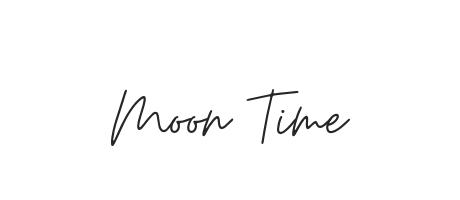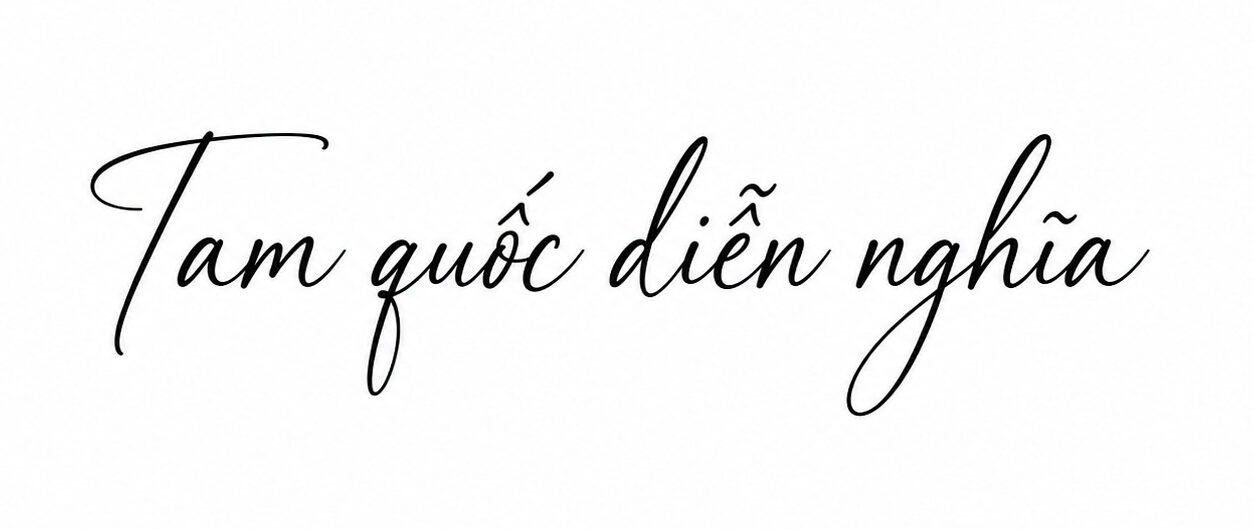
Font MoonTime là gì?
MoonTime font là một bộ phông chữ thuộc dòng Signature Script (chữ viết tay dạng chữ ký) mang phong cách nhẹ nhàng, phóng khoáng và tràn đầy cảm xúc lãng mạn. Được thiết kế với các đường tà chữ lướt nhanh, độ nghiêng nhẹ tự nhiên cùng các nét nối mềm mại, MoonTime mô phỏng chân thực cảm giác chấp bút từ ngòi bút mực kim thanh mảnh. Phông chữ mang lại vẻ ngoài tinh tế, tao nhã, giúp các sản phẩm thương mại dễ dàng tiếp cận người xem bằng sự mộc mạc và chân thành.
Trong nghệ thuật xây dựng thương hiệu thời trang và làm đẹp, MoonTime được ưa chuộng nhờ khả năng tạo điểm nhấn cá nhân độc đáo. Tuy nhiên, các nét vươn lên (ascenders) và kéo dài xuống (descenders) của bản gốc quốc tế thường bị va chạm với các dấu thanh tiếng Việt như dấu hỏi, ngã, nặng. Bản Việt hóa do In Viva chọn lọc đã được căn chỉnh khoảng cách an toàn cho hệ thống dấu tiếng Việt theo chuẩn Unicode, hỗ trợ nhà thiết kế dàn trang hài hòa mà không làm đứt gãy nhịp điệu tự nhiên của con chữ.
Lưu ý: MoonTime có cấu trúc nét chữ dạng chữ ký thanh mảnh. Khi thiết kế tiêu đề trên bề mặt bao bì tối màu, bạn nên ưu tiên kết hợp kỹ thuật ép kim nhũ vàng cát hoặc nhũ bạc mờ để đường nét chữ ký nổi bật sắc sảo.
5 ứng dụng MoonTime Font Việt hóa trong thiết kế và in ấn
Nhờ phong cách chữ viết tay mềm mại, thanh thoát cùng các đường nét mang cảm giác thủ công, MoonTime Font Việt hóa được ứng dụng linh hoạt trên nhiều sản phẩm bao bì và quà tặng doanh nghiệp theo hướng tinh tế, giàu cảm xúc:
- Thiết kế bao bì hộp mỹ phẩm và tinh chất chăm sóc da: Font MoonTime phù hợp để thể hiện tên thương hiệu, tên dòng sản phẩm trên hộp giấy Ivory, hộp carton lạnh hoặc bao bì mỹ phẩm cao cấp. Nét chữ nhẹ nhàng giúp sản phẩm tạo cảm giác thanh lịch, phù hợp với ngành làm đẹp.
- Sản xuất bao bì nến thơm và tinh dầu thư giãn: Khi kết hợp cùng giấy mỹ thuật có vân, kỹ thuật ép kim hoặc phủ UV, Font MoonTime giúp nhãn sản phẩm và hộp quà mang phong cách ấm áp, tinh tế, phù hợp với các dòng sản phẩm chăm sóc không gian sống.
- In ấn thiệp cảm ơn và ấn phẩm thương hiệu: Những câu chúc, thông điệp tri ân hoặc lời nhắn gửi sử dụng Font MoonTime tạo cảm giác gần gũi, giúp doanh nghiệp xây dựng sự kết nối với khách hàng thông qua các sản phẩm như Thank You Card, voucher hoặc thiệp đính kèm đơn hàng.
- Trang trí túi giấy thời trang và sản phẩm boutique: Logo sử dụng Font MoonTime trên túi giấy Kraft trắng, giấy Ivory hoặc giấy mỹ thuật giúp các thương hiệu thời trang, phụ kiện và làm đẹp thể hiện phong cách nhẹ nhàng, cao cấp.
- Khắc laser quà tặng cá nhân hóa: Font MoonTime có thể ứng dụng trên sổ tay bìa da, bình giữ nhiệt, bút ký hoặc hộp gỗ. Các đường nét uốn lượn giúp sản phẩm quà tặng trở nên độc đáo và mang dấu ấn riêng của người nhận.
5 lưu ý khi sử dụng MoonTime Font Việt hóa
Để Font MoonTime Việt hóa giữ được vẻ đẹp mềm mại và đảm bảo độ sắc nét khi sản xuất thực tế, designer cần chú ý:
- Ưu tiên sử dụng MoonTime Bold Font khi in thực tế: Với các phiên bản có nét chữ quá mảnh, khả năng mất nét có thể xảy ra khi in trên giấy sần hoặc chất liệu hút mực. Biến thể MoonTime Bold Font phù hợp hơn cho logo, tên thương hiệu hoặc chữ cần tạo điểm nhấn.
- Tối ưu đường Path khi gia công dập nổi: Khi sử dụng Font MoonTime làm logo trên hộp quà cao cấp, các đường cong, nét nối và phần đuôi chữ kéo dài cần được xử lý vector cẩn thận để khuôn dập thể hiện rõ chi tiết.
- Điều chỉnh khoảng cách ký tự (Kerning): Các chữ viết tay thường có nhiều nét nối liền nhau. Designer nên cân chỉnh khoảng cách giữa từng ký tự, đặc biệt với tên thương hiệu hoặc câu chúc dài để tránh tình trạng chữ bị chồng nét.
- Kiểm soát kích thước chữ khi in: Font MoonTime phù hợp nhất với logo, tiêu đề hoặc slogan ngắn từ 2 – 5 từ. Không nên sử dụng cho đoạn văn bản dài vì các nét trang trí có thể làm giảm khả năng đọc.
- Convert font trước khi gửi xưởng: Trước khi xuất file sản xuất, nên chuyển Font MoonTime thành dạng vector bằng lệnh Create Outlines để hạn chế lỗi thiếu font, sai ký tự hoặc thay đổi kiểu chữ khi mở file trên hệ thống khác.